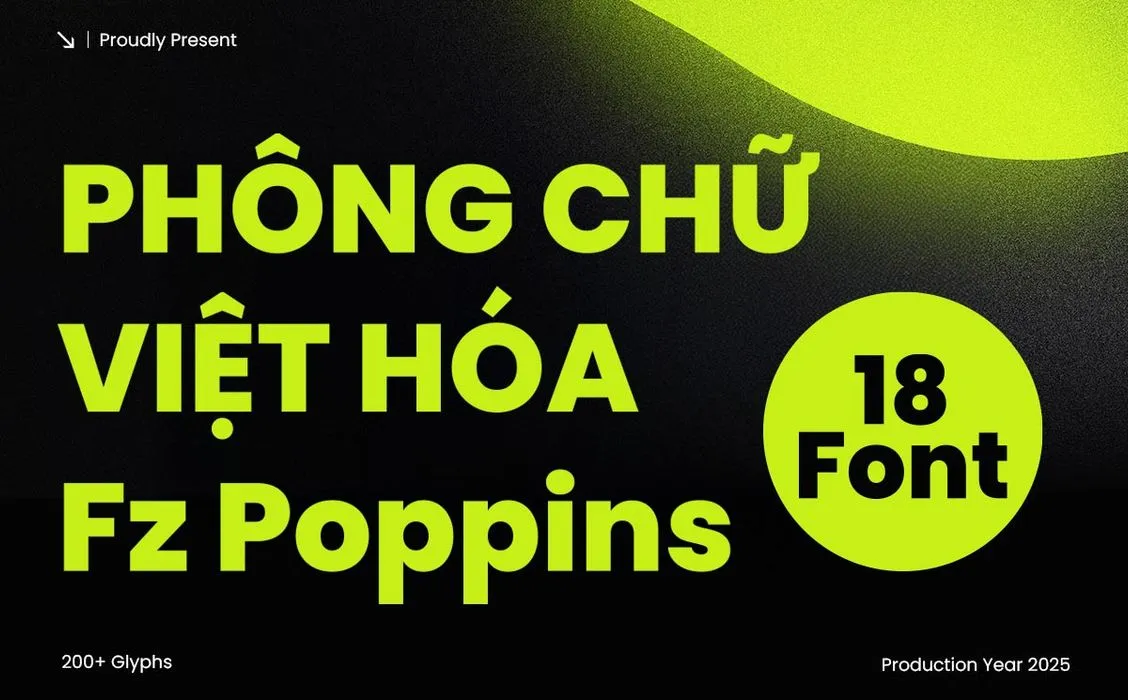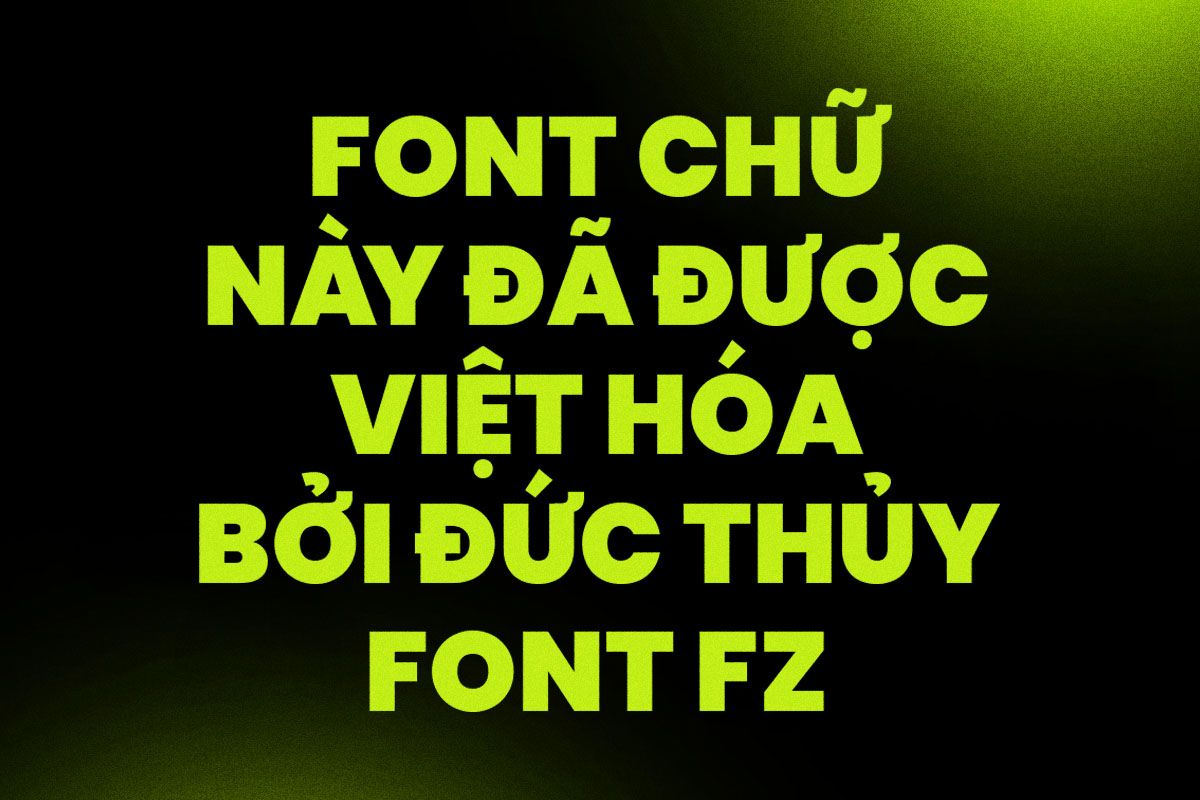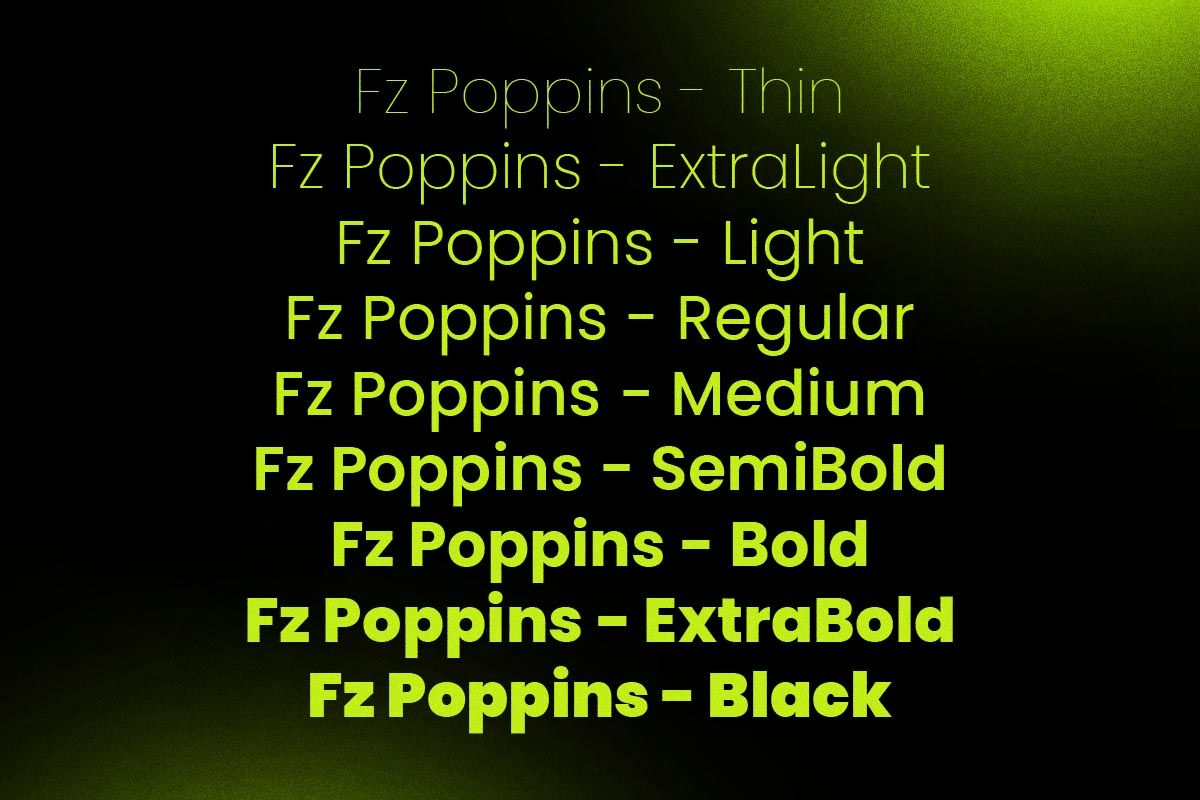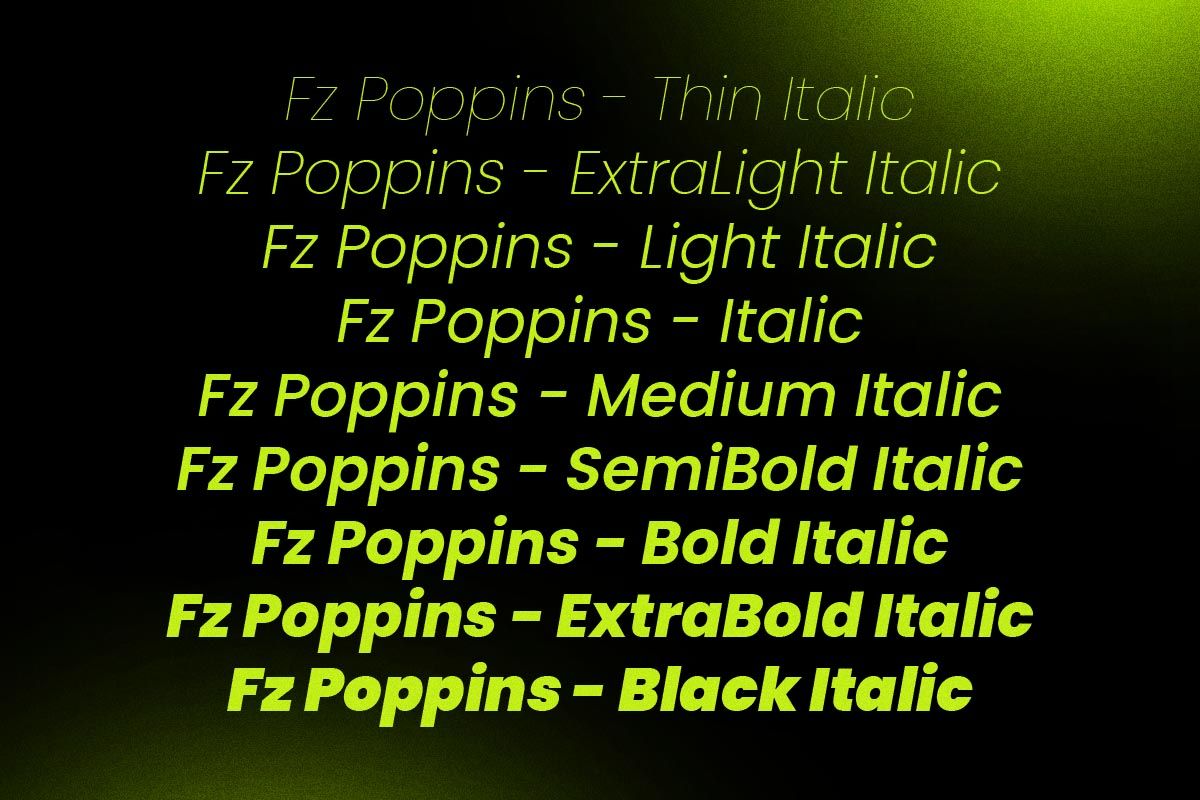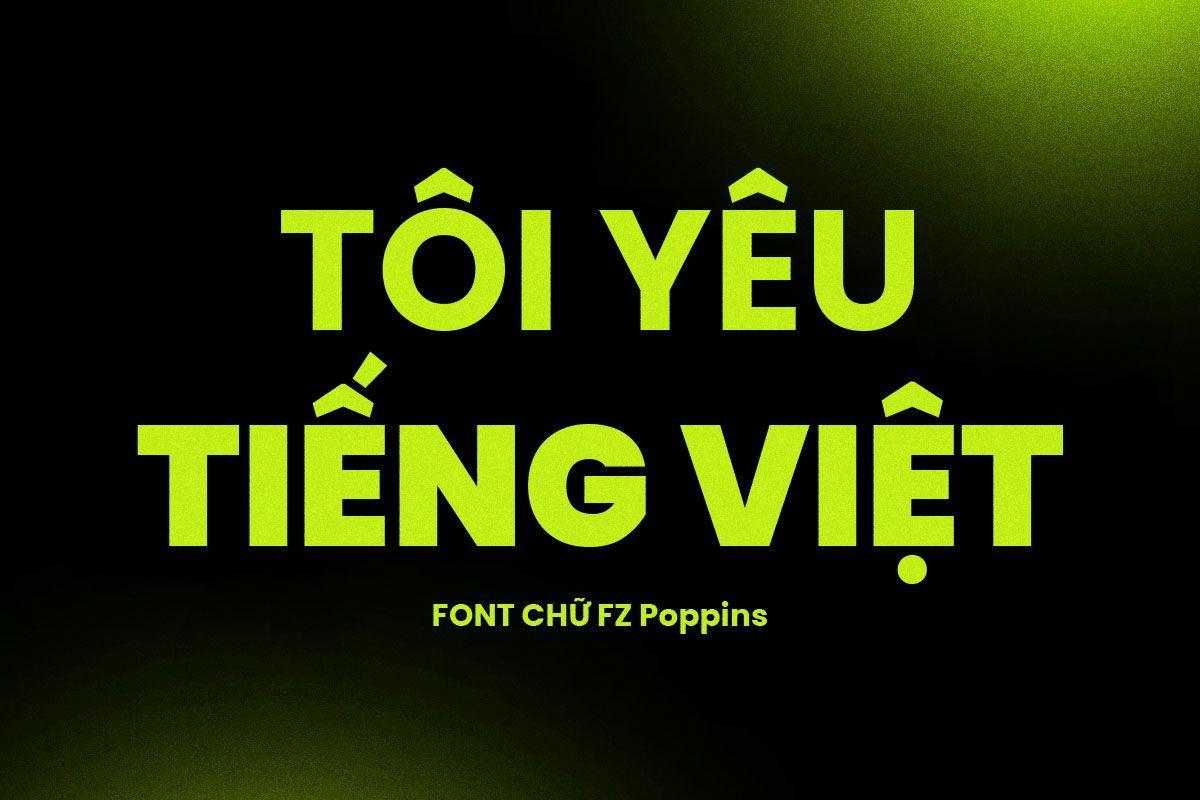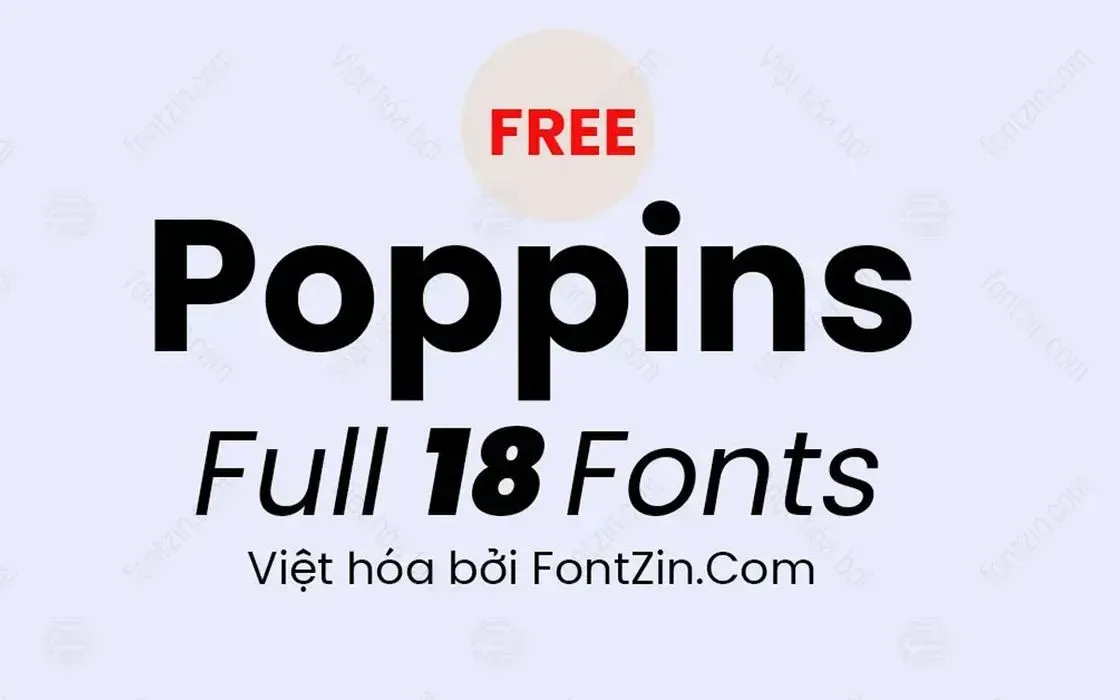
FZ Poppins là phiên bản Việt hóa của font Poppins, một kiểu sans-serif (không chân) nổi tiếng với thiết kế hiện đại, hình học và tối giản. Font được xây dựng dựa trên các hình tròn hoàn hảo và đường thẳng dứt khoát, mang lại cảm giác cân đối, thân thiện và dễ đọc trong mọi kích thước hiển thị – từ tiêu đề lớn cho đến đoạn văn bản nhỏ.
Toàn bộ bộ chữ mang đậm tinh thần thiết kế flat, minimalism – rất phổ biến trong giao diện người dùng (UI/UX), website, ứng dụng di động, bài thuyết trình, infographics, và cả các thiết kế mang tính thương hiệu công nghệ, startup.
Font gốc Poppins được thiết kế bởi Indian Type Foundry, phát hành miễn phí qua Google Fonts. Nó hỗ trợ rất nhiều trọng lượng chữ (từ Thin đến Black) và có độ tương thích cao với các hệ điều hành và trình duyệt web.
Phiên bản Việt hóa FZ Poppins được thực hiện bởi nhóm FZ (FontZin / Fontzone) – một cộng đồng và nhóm Việt hóa font chữ uy tín tại Việt Nam. Bộ font được tinh chỉnh kỹ lưỡng, bổ sung đầy đủ dấu tiếng Việt và đảm bảo tính đồng bộ với thiết kế gốc, giúp người dùng sử dụng mượt mà trong mọi phần mềm thiết kế như Photoshop, Illustrator, Canva hay PowerPoint.
Nếu bạn đang tìm một font không chân, hiện đại và dễ ứng dụng, thì FZ Poppins là lựa chọn lý tưởng cho các thiết kế cần sự chuyên nghiệp, sạch sẽ và tối giản, đặc biệt trong lĩnh vực công nghệ, giáo dục và truyền thông số.